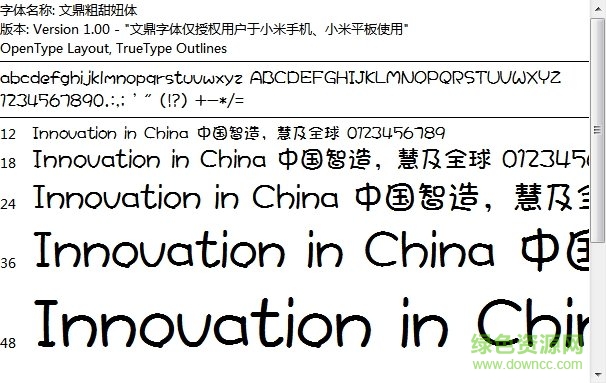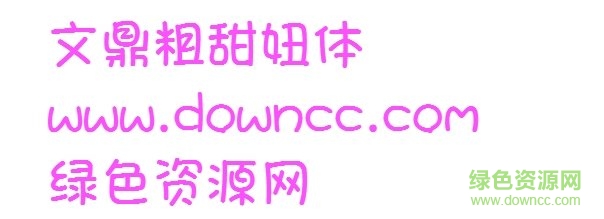
文鼎粗甜妞體是華為榮耀手機(jī)中的系統(tǒng)字體,也是文鼎甜妞體的升級版本,補充了原有的字庫,支持繁簡體輸入,可愛的造型讓你的手機(jī)擁有不一樣的界面,綠色資源網(wǎng)今日推薦!
文鼎甜妞體系列,是充滿孩童般童趣的天真氣息,設(shè)計發(fā)想是針對使用者年齡而設(shè)計的,特別是少女、兒童等年輕族群的刊物,印刷相關(guān)產(chǎn)品使用的字型。 文鼎甜妞體的筆型渾厚圓潤,字構(gòu)活潑可愛,不同于一般傳統(tǒng)字型的刻版印象。具有青春活力、甜美可愛、自由、創(chuàng)新的特色。
文鼎甜妞體有三種粗細(xì)字體,本系列包括文鼎粗甜妞體、文鼎特甜妞體和文鼎甜妞卡通字體,均是采用了兒童字體的童真趣味,讓文字更加令人印象深刻。